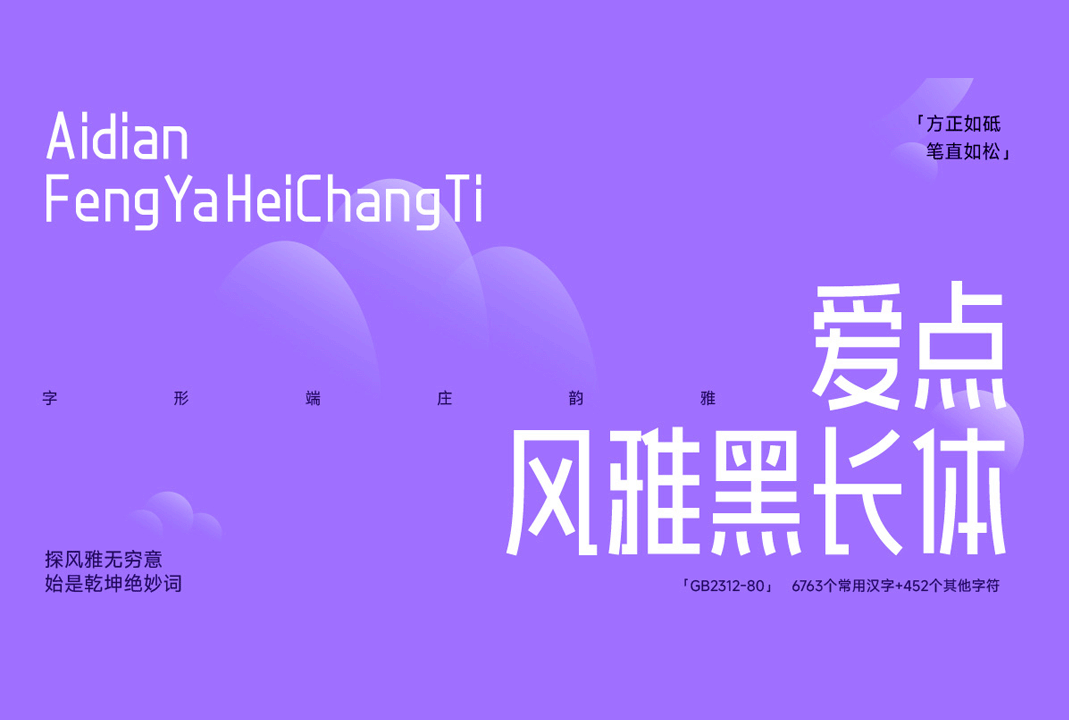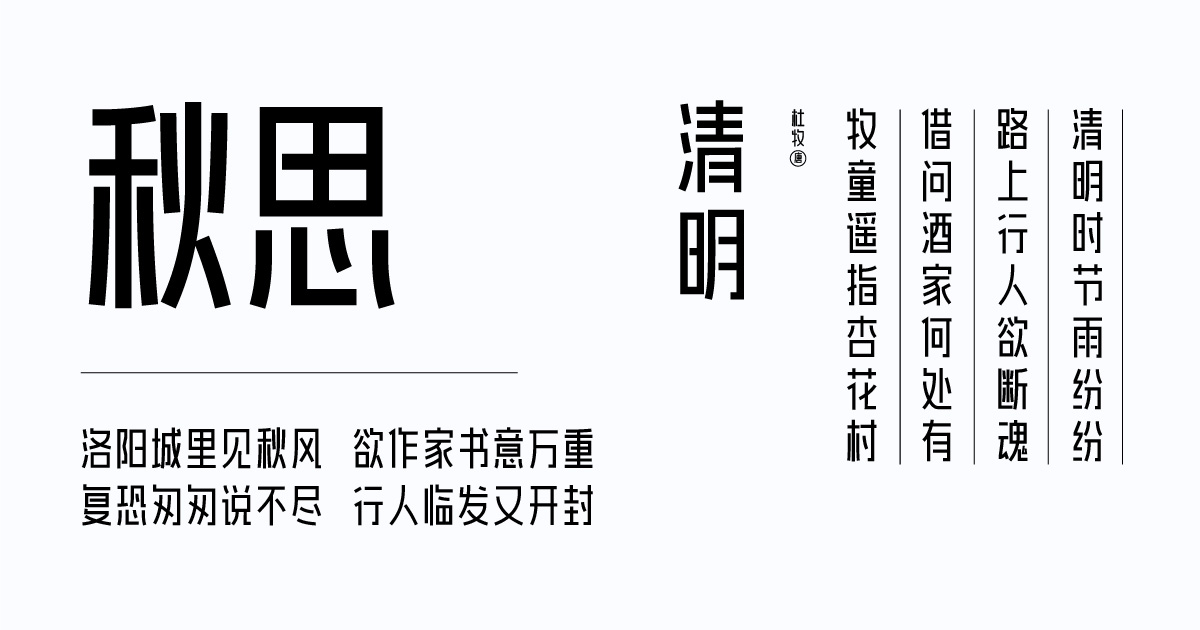
爱点风雅黑长体(AidianFengYaHeiChangTi)_中文免费字体下载
爱点风雅黑长体是爱点字库设计发布的一款免费商用中文字体,该字体字形结构端庄大气又不失优雅,整体结构饱满,空间布局均衡,规整的方块化轮廓让排版更加整齐,字库字符数共7215个,含6763个常用汉字+452个其他字符,可满足日常大部分使用场景。